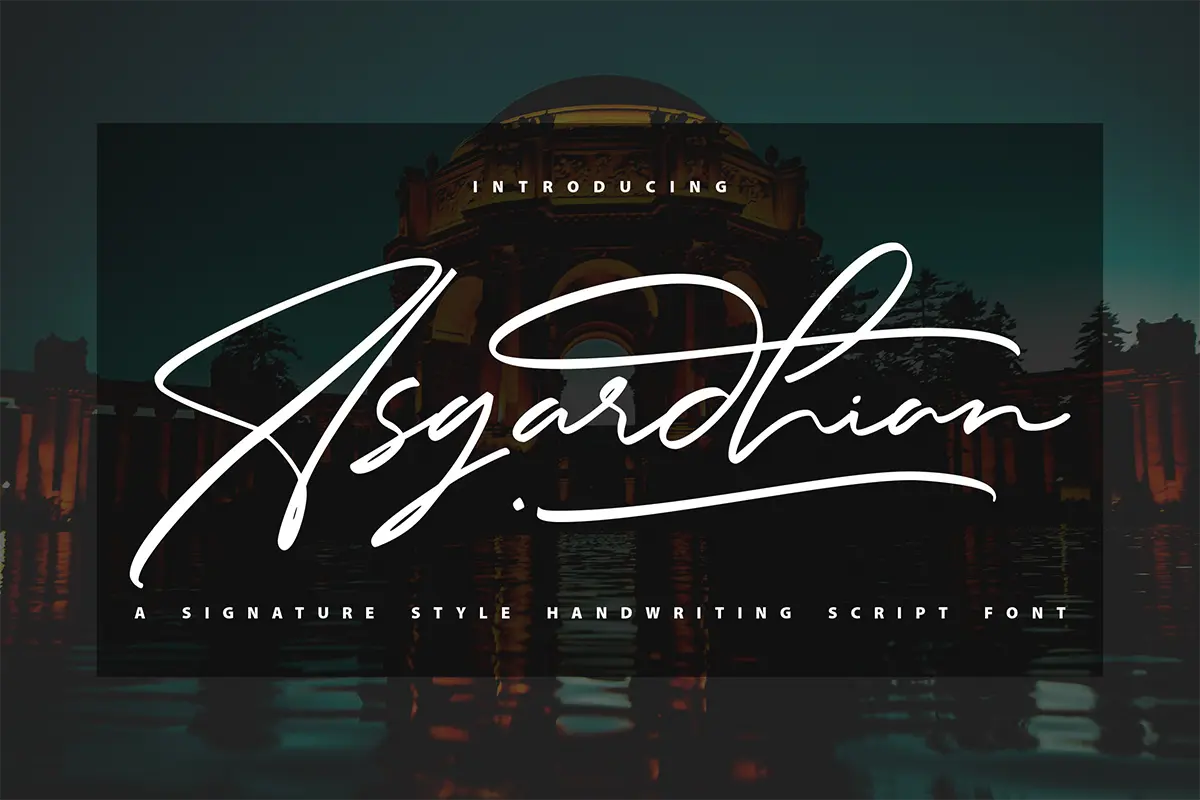
فونت دست نویس شیک و زیبا
فونت Asgardhian یک فونت دست نویس فوقالعاده زیبا و استایل شیک است که برای تیترها و پروژههای لوگوتایپ طراحی شده. این فونت با ظاهری مدرن و منحنیهای جذاب، جلوهای خاص و حرفهای به طرحهای شما میبخشد.
⭐ ویژگیهای محصول:
- سبک: Handwritten Font – فونت دستنویس مدرن و شیک
- طراحی: زیبا، استایلدار و مناسب برای تیترها و لوگوتایپها
- PUA Encoded: دسترسی آسان به تمامی گلیفها و سوئشها
🎯 موارد استفاده:
- طراحی لوگوهای خاص و هنری
- تیترها و سرتیترهای تبلیغاتی جذاب
- کارتهای تبریک و دعوتنامههای شیک
- پوسترها و بنرهای مدرن
- بستهبندی محصولات لوکس و خلاقانه